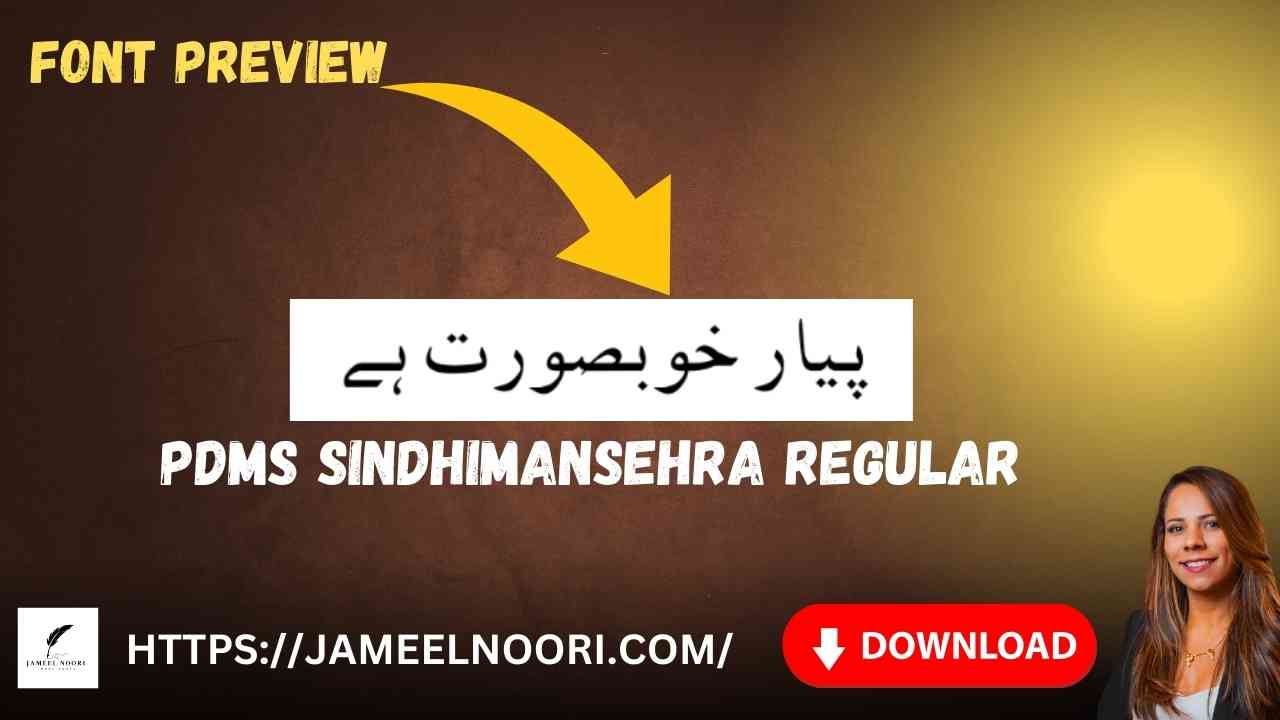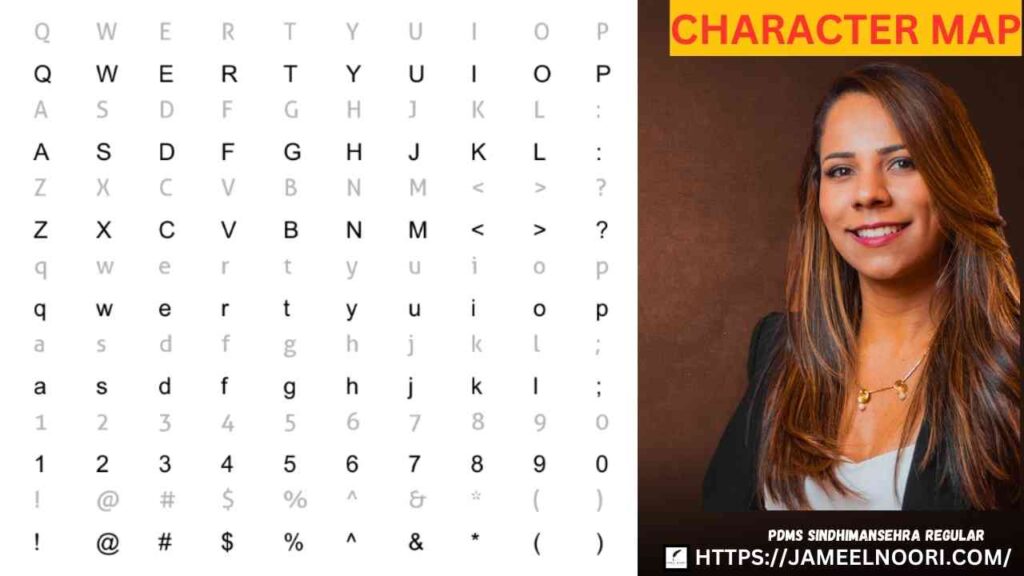
Download Urdu font PDMS SindhiMansehra Regular – Complete Guide
Download Urdu font PDMS SindhiMansehra Regular ek popular aur reliable Urdu font hai jo specially Pakistan aur India ke users ke darmiyan bohot demand me hai. Ye font apne elegant aur stylish design ki wajah se na sirf Urdu typing ke liye perfect hai, balki Roman aur Sindhi typing me bhi smooth aur professional output deta hai. Iska use aksar designers, publishers aur students karte hain jo apne projects me readability aur modern look chahte hain.
Features of Download Urdu font PDMS SindhiMansehra Regular
PDMS SindhiMansehra Regular ke features isay popular aur reliable banate hain.
• High Quality TrueType Font: Yeh font sharp aur clean text rendering provide karta hai.
• User-Friendly Design: Har character easily readable hai, aur typing experience smooth hai.
Benefits of Using Download Urdu font PDMS SindhiMansehra Regular
PDMS SindhiMansehra Regular ka use karke aap apne Urdu typing aur designing skills ko enhance kar sakte hain:
• Professional Documents: Urdu aur Roman text documents professional lagte hain.
• Creative Designs: Posters, banners aur social media graphics me use karna easy hai.
• Educational Material: Students aur teachers ke liye notes aur presentations easy aur readable bante hain.